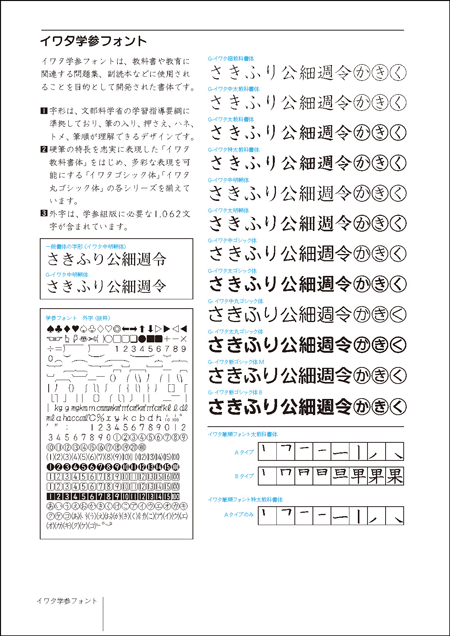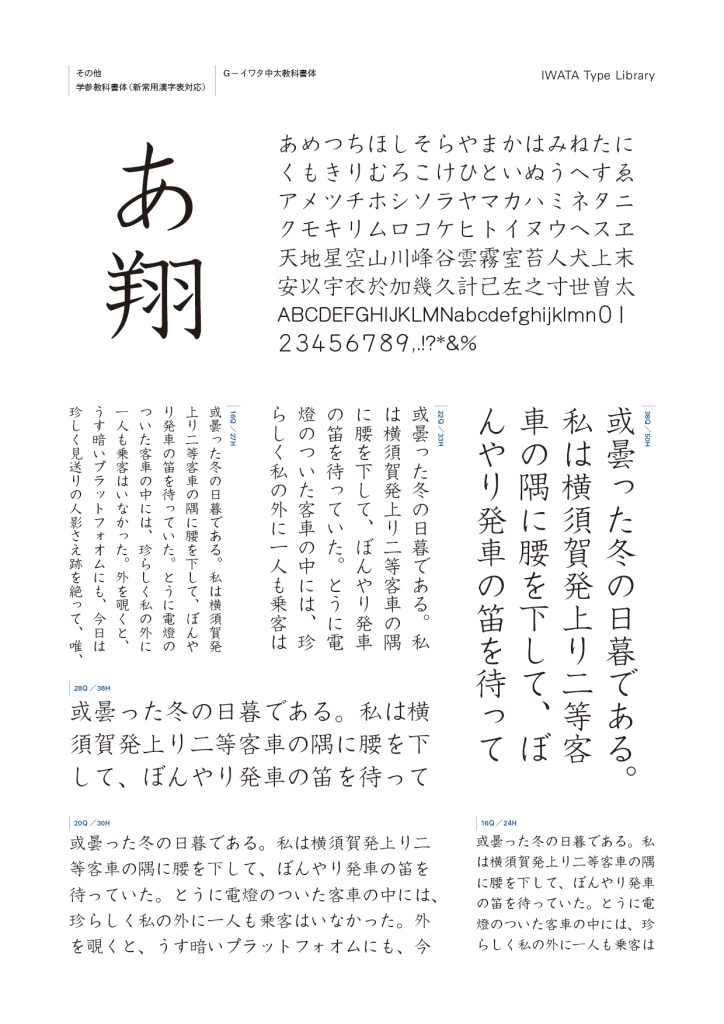
学参教科書体(新常用漢字表対応)
G−イワタ中太A教科書体
G−イワタ細教科書体
G−イワタ中太教科書体
G−イワタ太教科書体
G−イワタ特太教科書体
教科書等の教育に関する著作物、あるいは教育現場にて制作される問題集、副読本等の制作に使用されることを目的にとして開発されました。
教育漢字1,006文字についてハネ・トメ・押さえ・筆順等を文部科学省の学習指導要領の字形に準拠して制作されたフォントです。小学校の教科書・ドリル・学習参考書に最適です。プロフェッショナルな学習組版に必要な外字1,036文字も付いています。